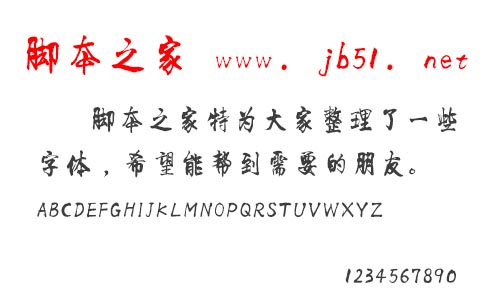
劍客毛筆行書是一款很受歡迎的字體,它就像使用毛筆字寫出來的行書,字體俊逸灑脫,美觀又實用。當然你還可以用來練字,感興趣的朋友千萬不要錯過了。
劍客毛筆行書是一款適用性非常廣泛的中文簡體字體,該字體將書法感和設計融為一體,其連筆張弛有度,結體清麗優(yōu)美,整體效果出色,能夠應用于文本裝潢、信息展示、網頁設計、篆刻制模、數據制作、裝潢設計、計算藝術設計、視覺設計、字帖等一切合法應用場景。